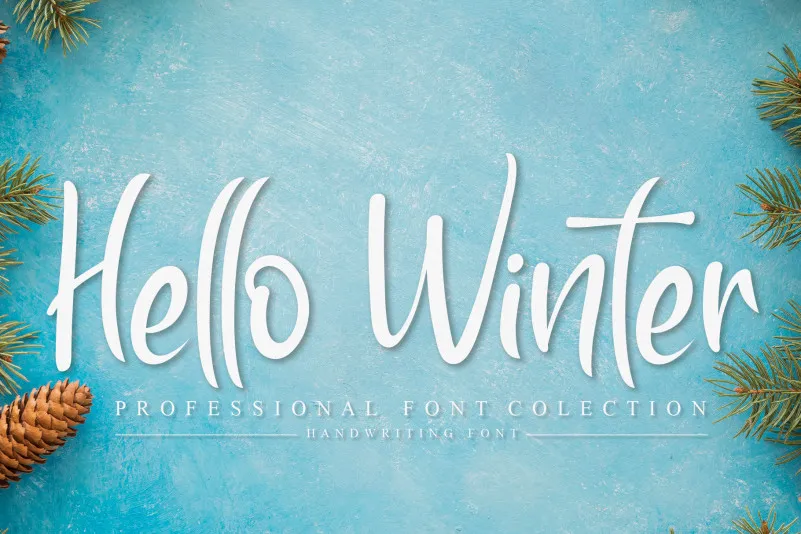
Hello Winter Script Font – Download Grátis
A fonte ‘Hello Winter Script Font’ é uma delícia para os olhos e perfeita para aqueles que buscam algo autêntico e sofisticado. Inspirada em escrita manual, ela traz um ar descontraído e trendy que combina tão bem com uma infinidade de usos. É perfeitamente adequada para criar marcas inovadores, convites de casamento, parágrafos chamativos, camisetas personalizadas, assinaturas de documentos, sinais publicitários, etiquetas e até mesmo cartazes ou material promocional. Com sua textura natural e estilo elegante, a ‘Hello Winter Script Font’ não apenas se torna uma opção versátil para diversos projetos gráficos, mas também adiciona um toque único e pessoal ao seu design. Seja você que está buscando expressar suas ideias de maneira única ou criou um novo projeto que necessite de personalização, esta fonte oferece a liberdade para fazer isso em um estilo tão atraente e autêntico quanto ela é original.